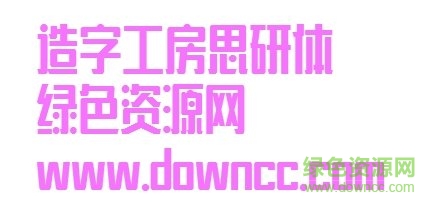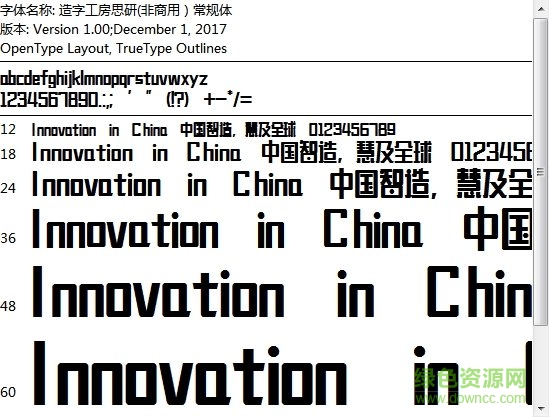
造字工房思研體是2017年推出的一款黑體字體,將部分漢字筆畫(huà)變成小圓點(diǎn),同時(shí)黑化了字跡,顯得更為醒目嚴(yán)肅,造型更加端方,來(lái)綠色資源網(wǎng)免費(fèi)體驗(yàn)吧!
造字工房于2017年年末發(fā)布了全新的15款新字體分別是造字工房凌毅 、卓黑 、喜月 、念真 、思研 、文尚 、星巖 、景悅 夢(mèng)緣 、梵宋 、素白 、羽逸 、逸鋒 、錦華 以及造字工房鼎黑常規(guī)體。造字工房的字體用于標(biāo)題及PPT設(shè)計(jì)。
造字工房思研體,其字形瘦長(zhǎng)、工整毓秀,點(diǎn)畫(huà)的圓形處理令其不失活潑生動(dòng)之感,特點(diǎn)鮮明,在兼具黑體結(jié)構(gòu)嚴(yán)謹(jǐn)之外,平添幾分稚拙俏皮。適用于大標(biāo)題、品牌廣告宣傳等需要強(qiáng)力視覺(jué)表現(xiàn)的環(huán)境。